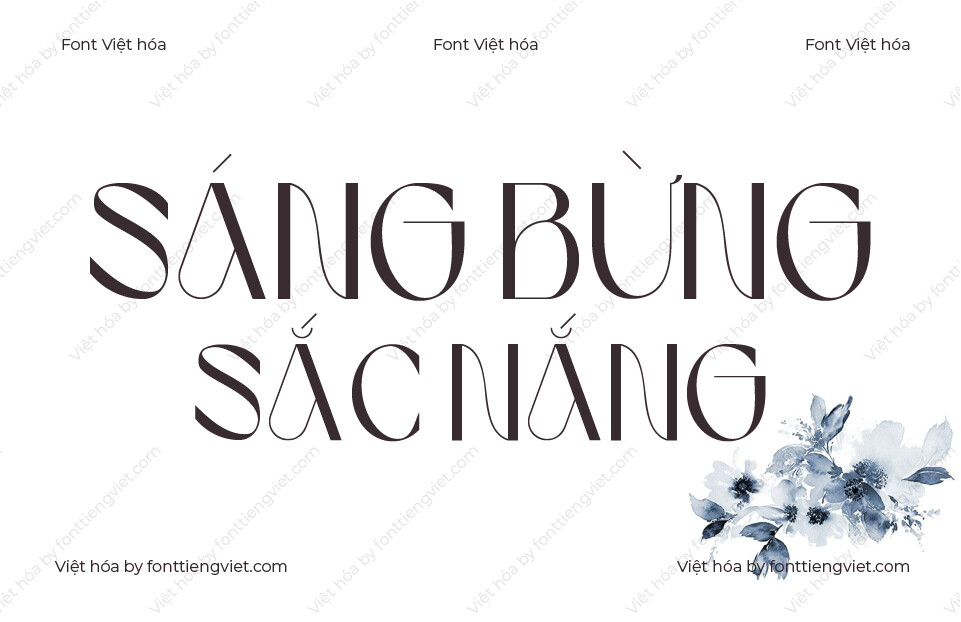
Font Việt hóa 1FTV VIP Royale Brone
Tải Font Việt hóa 1FTV VIP Royale Brone Miễn Phí Cho Thiết Kế Sang Trọng
Trong thế giới thiết kế đồ họa hiện đại, việc lựa chọn một bộ chữ phù hợp đóng vai trò quyết định đến sự thành công của một tác phẩm nghệ thuật. Đối với những nhà sáng tạo nội dung tại Việt Nam, nhu cầu tìm kiếm các bộ chữ đẹp, tinh tế và quan trọng nhất là phải hỗ trợ đầy đủ tiếng Việt luôn là ưu tiên hàng đầu. Bộ Font Việt hóa 1FTV VIP Royale Brone chính là một trong những sự lựa chọn tuyệt vời nhất hiện nay dành cho những ai đang tìm kiếm phong cách hoàng gia và đẳng cấp. Khi bạn sử dụng Font Miễn Phí để trang trí cho các dự án của mình, bạn sẽ nhận thấy sự khác biệt rõ rệt về mặt thẩm mỹ cũng như khả năng truyền tải thông điệp mạnh mẽ. Đây là một bộ font chữ mang đậm nét cổ điển nhưng vẫn giữ được sự hiện đại cần thiết cho các ấn phẩm truyền thông ngày nay.
Đặc điểm nổi bật của Font Việt hóa 1FTV VIP Royale Brone
Bộ font này được cộng đồng thiết kế đánh giá cao nhờ vào đường nét trau chuốt và tỉ mỉ trong từng ký tự. Font Việt hóa 1FTV VIP Royale Brone sở hữu các nét thanh mảnh kết hợp cùng những đường cong uốn lượn đầy nghệ thuật, tạo nên một tổng thể hài hòa và quý phái. Đặc biệt, quá trình Việt hóa đã được thực hiện vô cùng kỹ lưỡng, đảm bảo các dấu câu tiếng Việt không bị lỗi hiển thị hay mất nét khi gõ văn bản dài. Điều này giúp cho các bạn học sinh, sinh viên và giáo viên dễ dàng ứng dụng vào việc làm slide bài giảng, thiết kế thiệp mời hay các tài liệu học tập một cách chuyên nghiệp nhất.
Tính ứng dụng linh hoạt trong giáo dục và đời sống
Không chỉ dừng lại ở các dự án thương mại, Font Việt hóa 1FTV VIP Royale Brone còn cực kỳ phù hợp cho môi trường học đường. Bạn có thể sử dụng bộ chữ này để thiết kế tiêu đề cho các báo tường, bìa sách giáo khoa hoặc các chứng chỉ khen thưởng cho học sinh. Với phong cách trang trọng vốn có, nó giúp tôn vinh những thành tựu và tạo cảm hứng học tập cho người xem. Sự rõ ràng của các chữ cái giúp việc đọc trở nên dễ dàng hơn, đồng thời tạo ra một giao diện thân thiện và dễ tiếp cận cho các em nhỏ.
Lý do bạn nên sở hữu Font Việt hóa 1FTV VIP Royale Brone ngay hôm nay